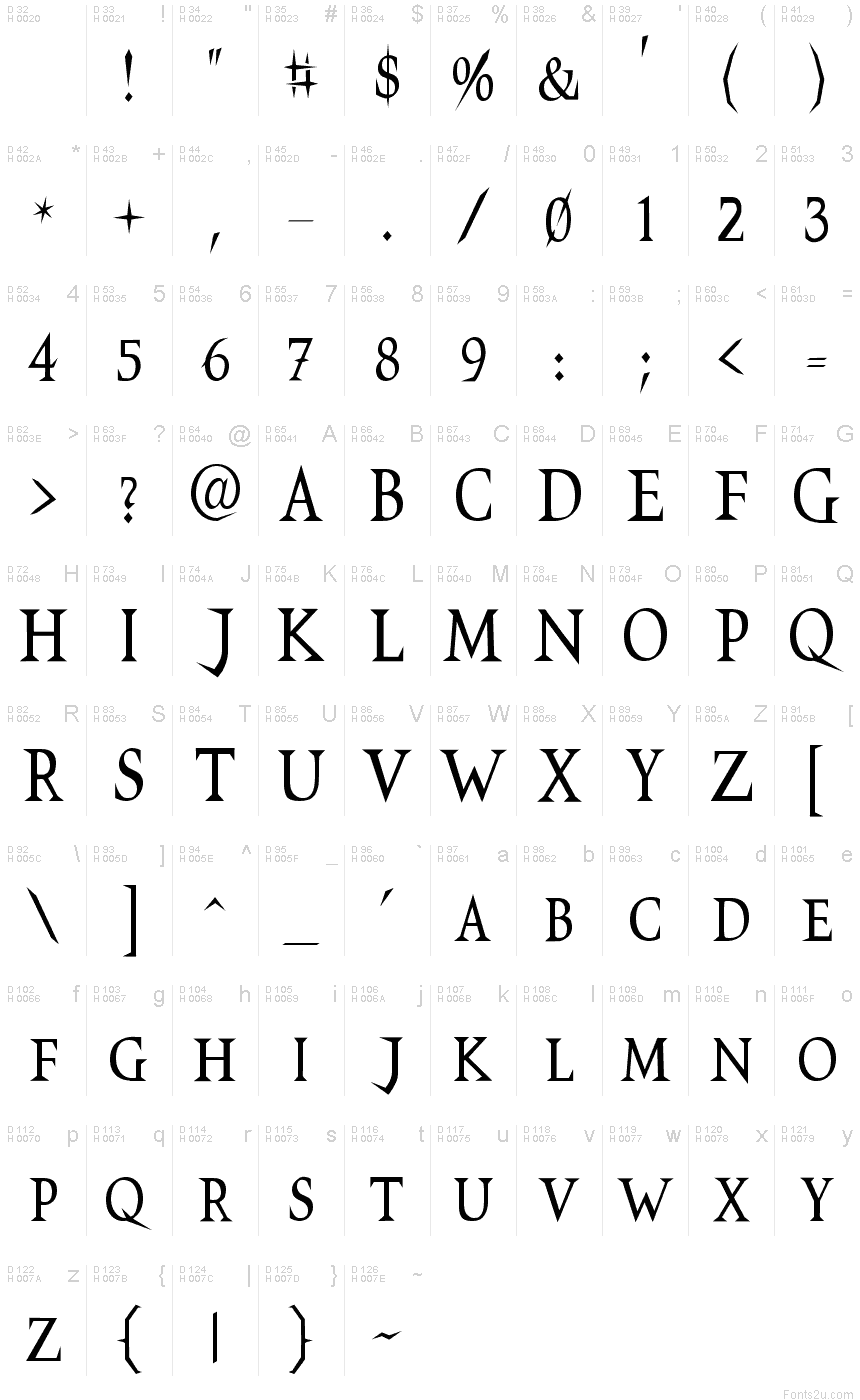
Podgląd czcionki VTCSwitchbladeRomanceTall
VTC Switchblade Romance Tall od V.T.C. Vigilante Typeface Corporation to darmowy, retro font typu display, który przywodzi na myśl teatralny klimat dawnych plakatów. Litery sprawiają wrażenie wydłużonych i arystokratycznych, łącząc ostre, klinowe szeryfy z płynnymi krzywiznami, dzięki czemu wielkie litery nabierają formalnego, lekko melodramatycznego wyrazu.
Krój sprawdzi się na okładkach płyt, w tytułach filmów, menu barowych, na plakatach eventowych oraz w edytorialach modowych, gdzie potrzebna jest wysoka, wyrazista sylwetka liter. Jako darmowy font, świetnie nadaje się również do nagłówków, plansz tytułowych i monogramów, zwłaszcza gdy chcesz dodać odrobinę vintage glamour, nie przesadzając przy tym ze zdobieniami.